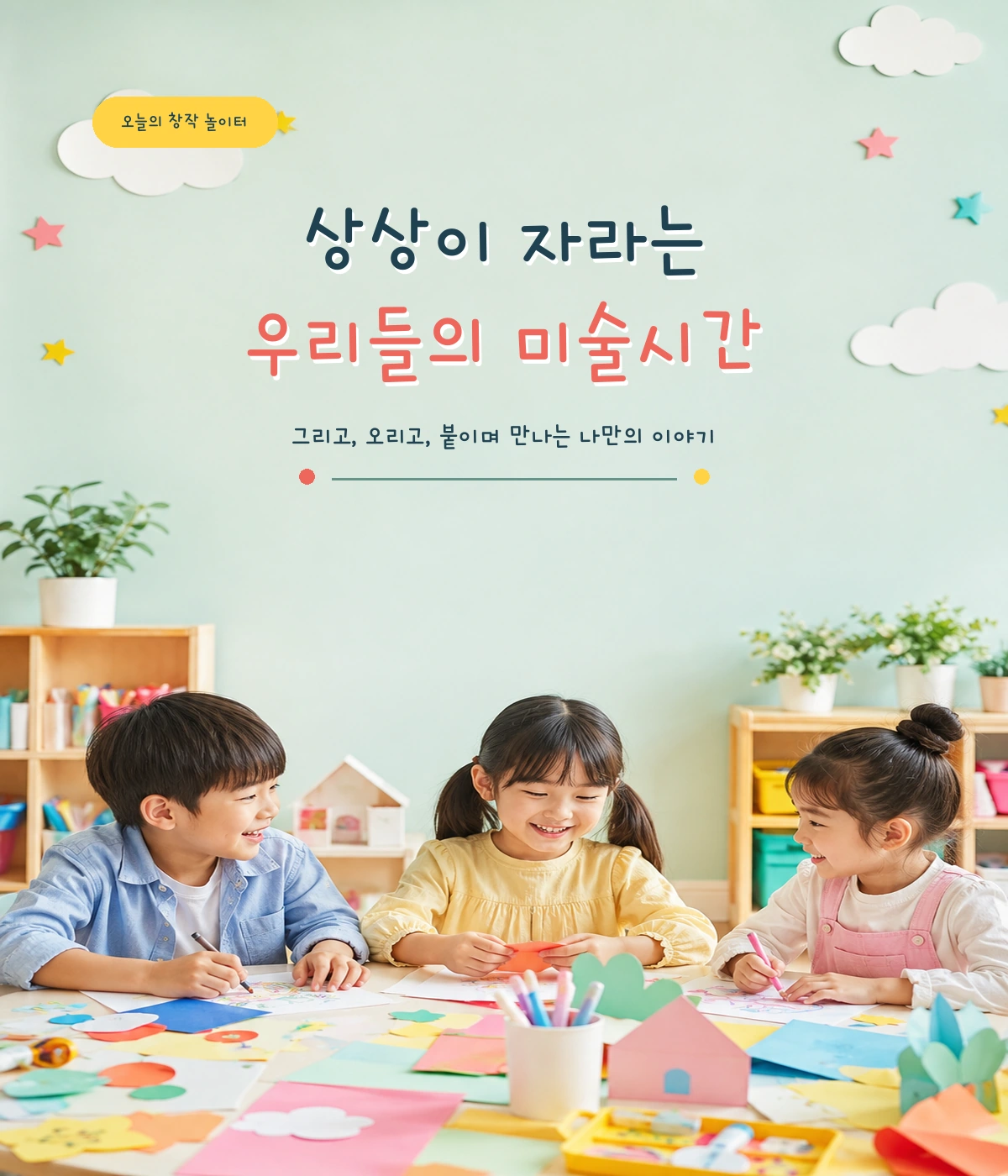
KCC도담도담체 — 한국저작권위원회에서 배포하는 무료 폰트입니다. 어린애가 탈 없이 잘 자란다는 순우리말처럼, 글자마다 리듬이 도는 어린이용 손글씨체
한국저작권위원회가 2018년 국민 손글씨 폰트 제작 사업으로 만들어 공유마당에 올린 서체입니다. 제작은 타이포디자인연구소가 맡았습니다.
이름의 뜻을 제작사가 밝혀 두었습니다. 건강하게 자라나다라는 뜻에서, 어린애가 탈 없이 잘 자라는 모양을 나타내는 순우리말을 폰트 이름으로 골랐다는 것입니다. 만든 방식도 적어 두었습니다. **어린이집과 유치원 등 관련 전문가의 의견을 수렴해 제작**했다는 것인데, 여기서 오해가 생기기 쉽습니다. 손글씨 폰트 사업의 결과물이지만 특정한 개인의 글씨를 받아 만든 것이 아니라 어린이용으로 새로 설계한 서체입니다.
파일에서 재어 보면 받침이 붙을 때 글자 높이가 달라지는 탈네모틀이라 손으로 쓴 리듬이 남아 있고, 획이 가늘어 자면을 채우는 비율은 낮습니다. 낱자는 가로로 퍼져 있습니다. 굵기는 하나이고 현대 한글 11,172자를 모두 담았습니다.
어린이 교재나 알림장, 동화처럼 아이를 향한 자리에 어울리고 격식 있는 문서에는 맞지 않습니다. 오픈 폰트 라이선스로 수정과 재배포가 가능하지만 출처 표시를 요구합니다.